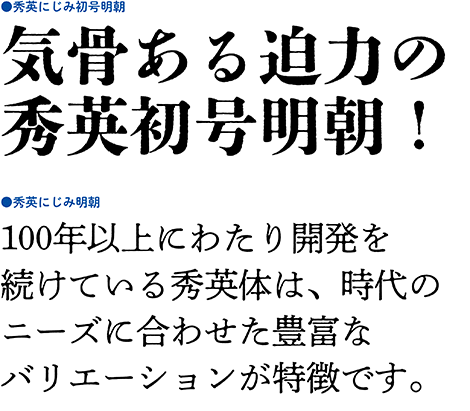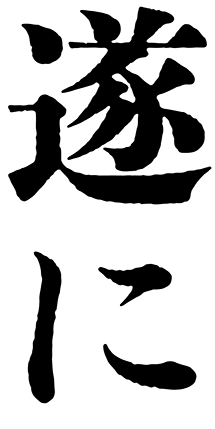
新たに「秀英にじみ初号明朝」を開発、アドビより提供開始
大日本印刷株式会社は、オリジナル書体「秀英体」の開発に明治時代から1世紀以上にわたって取り組んでおり、その時代のニーズに合わせ、またニーズを先取りしながら、常に新しい価値を社会と人々に提供し続けています。今回、活版印刷の風合いの再現が高く評価されている「にじみシリーズ」の新たなラインアップとして、「秀英にじみ初号明朝」を開発しました。
これに伴い、2017年からアドビ株式会社にライセンス提供している「秀英体」ファミリーに、「秀英にじみ明朝」と「秀英にじみ初号明朝」の2書体を追加します。アドビは、この新しい書体を「Adobe Creative Cloud」のフォントサービス「Adobe Fonts」のラインアップに追加し、10月27日より提供します。
「秀英にじみ明朝」
「秀英にじみ明朝」は、「にじみシリーズ」第1弾として開発した書体です。DNPが100年以上にわたって活版印刷で使用してきた「秀英体」が、印刷した紙の上でどのように表現されているか細かく分析し、その結果を“にじみ効果“として付与する専用プログラムを独自開発しました。このプログラムで「秀英明朝」に対して画像処理を行った上で、自然な“にじみ感”が出るよう、1字1字丁寧に調整を加えて完成させました。紙とインクの質感を思わせるような柔らかい表情を持ち、和菓子や工芸品、手作り品のパッケージなどで日本の伝統や美、レトロ感を演出する際などに最適です。
「秀英にじみ初号明朝」
秀英体の魅力がわかりやすい代表的な見出し用書体である「秀英初号明朝」に、活版印刷のようなインクの“にじみ効果”を持たせました。書籍・ポスター・Webサイトのタイトルや小見出しなど、大きな文字サイズで利用した際に良く映えるよう、“にじみ効果”の「太らせ量」や「ゆらぎ量」を調整しました。その“にじみ効果”が、「秀英初号明朝」の凛とした表情に柔らかくレトロな雰囲気を与え、より味わいある表現を演出しています。
また、「秀英にじみ初号明朝」は、アドビが開発する新書体「ヒグミン」と連動させて、「太らせ量」や「ゆらぎ量」を調整しており、「ヒグミン」の仮名と組み合わせる漢字書体としての利用も推奨されています。
遂に!にじみシリーズに「秀英初号明朝」が加わりました。
Adobe Fontsには、秀英体にじみシリーズから「秀英にじみ明朝」「秀英にじみ初号明朝」の2書体が加わり、秀英体ファミリーのうち19書体22フォントをお使いいただけるようになります。